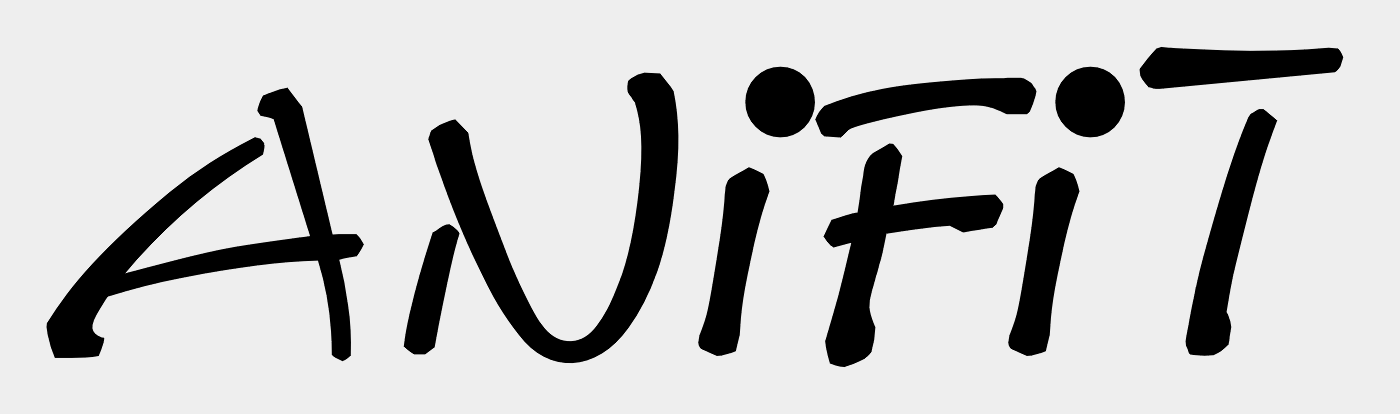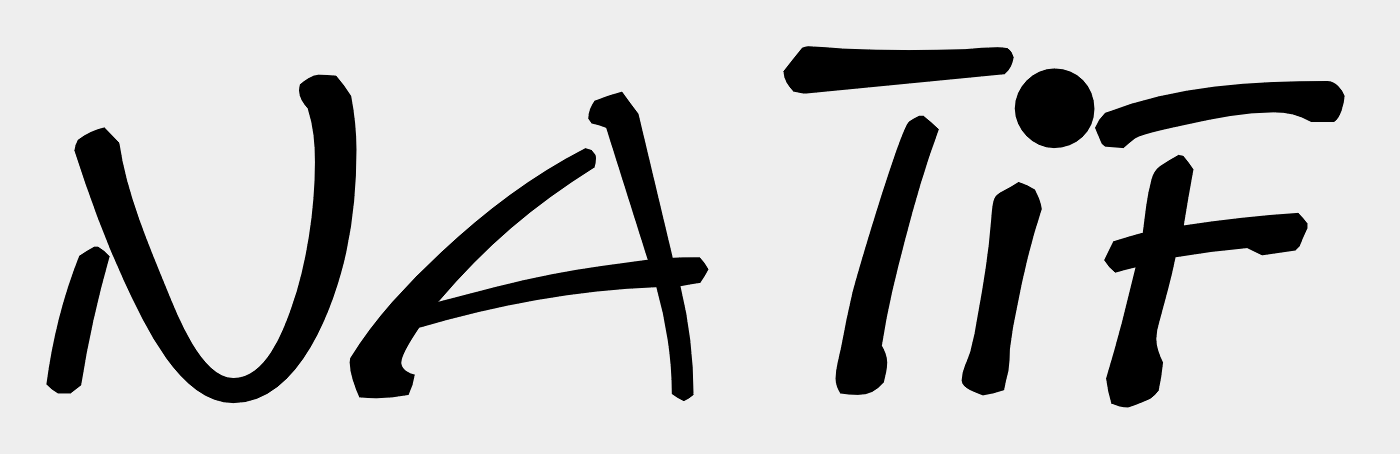
Schrift gesucht (NATIF)
ich bin auf der Suche nach eine Schrift.... vielleicht kann mir ja jemand helfen.
Die Comix Italic von Softmaker ist sehr ähnlich …
Original:
... oder:
Wahrscheinlich war eine von denen die Grundlage und dann wurde an den Pfaden gezupft :-?
Ist das denn aus einem Logo, oder wo kommt das her?
Das kommt aus dem Anifit-Logo (http://www.anifit.ch/), wie ich oben schon verraten habe :-P. Anifit vertreibt Tiernahrung über Berater à la Tupperware.
Wenn nur das Logo als Vektorgrafik gesucht wird: Das konnte bequem aus einem pdf extrahiert werden.
Hier noch eine ältere Version:
Hier sieht man ganz gut den Ursprung in Comix oder Le Obelix. Das Logo wurde begradigt und aufgedickt, es wird vermutlich keinen Font geben, der den neuen Formen entspricht.